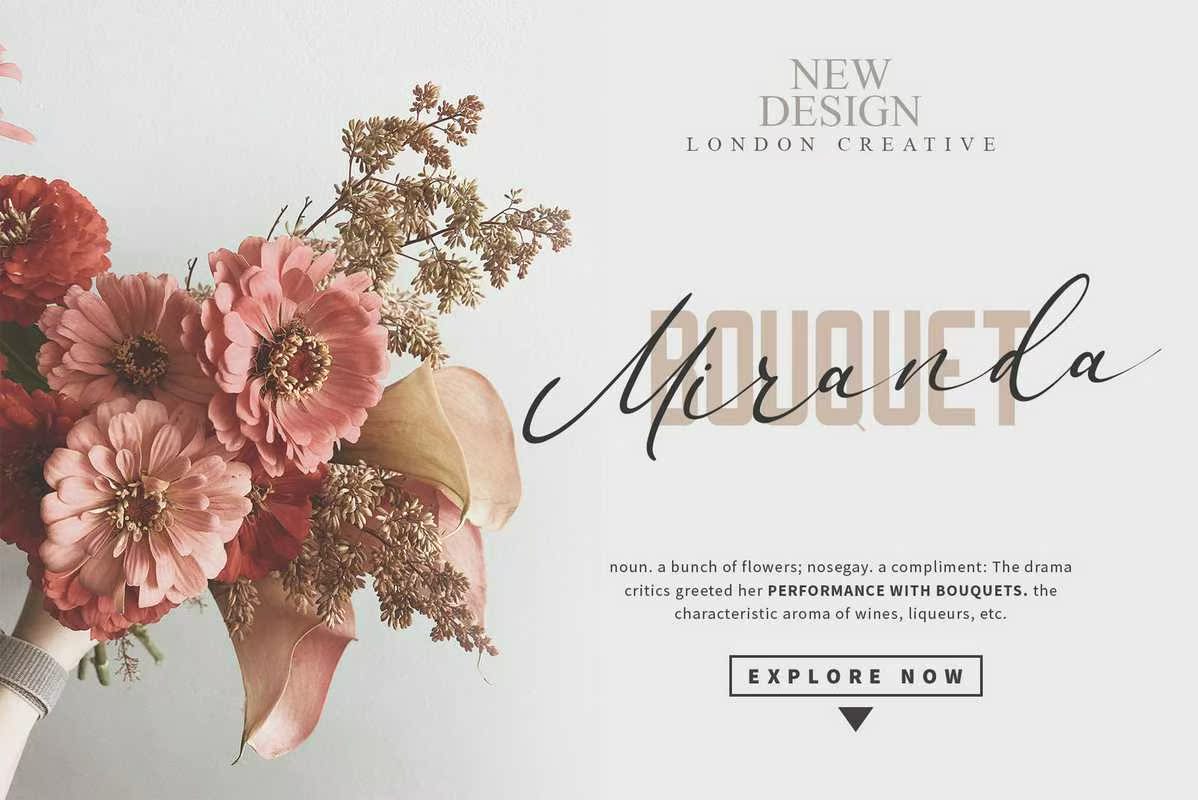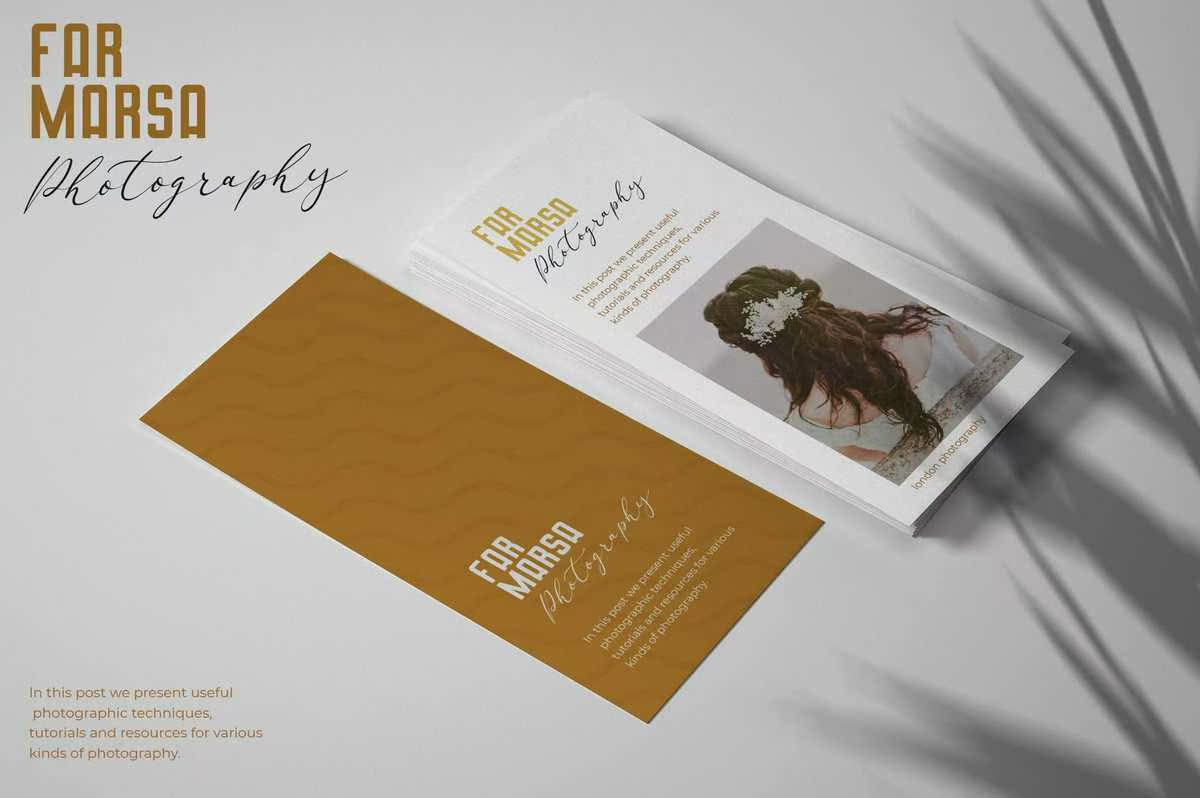
CaliforniaSignature FontDuo、SansSerif和ScriptTypefont。适合您的项目的文字和数字集合非常适合于标识、品牌设计、标识设计、数字字母艺术、T恤/服装、海报、杂志、标志、广告设计和任何设计需求。CaliforniaSignature FontDuo,SansSerif&ScriptTypefont。适合您项目的文字和数字集合非常适合于标识、品牌设计、标识设计、数字字母艺术、T恤/服装、海报、杂志、标志、广告设计和任何设计需求。